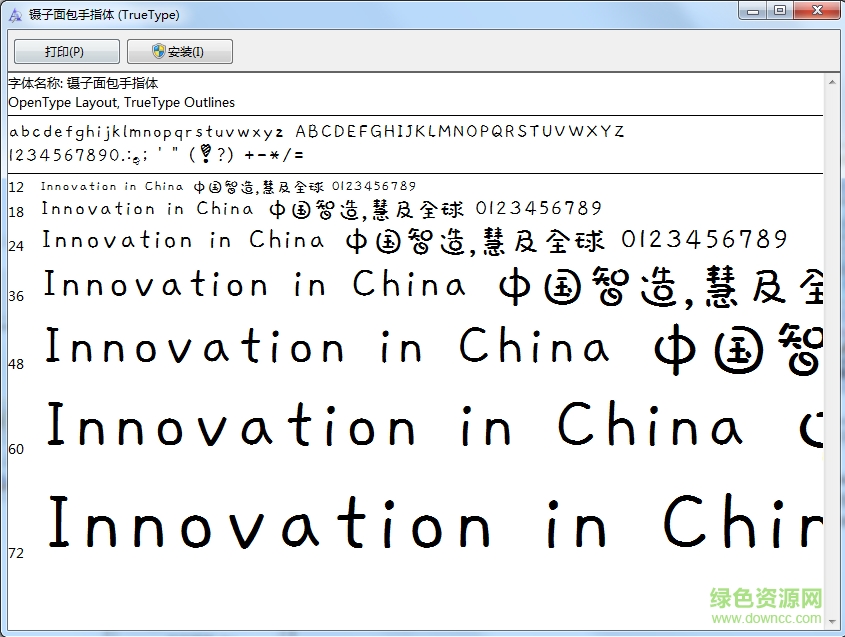
软件介绍 软件标签: 面包萌手指 卡通字体 面包萌手指是一款超卡哇伊的艺术字体,高仿面包的造型充满了童趣和可爱,让你感受各种小面包在字里行间的跳动,喜欢的朋友快来绿色资源网下载吧!面包萌手指字体介绍面包萌手指字体是一款卡通字体模板,该字体具有棱角圆润,字形饱满等特点,而且走着还在在字体笔画中加入了面包等图形。镊子面包萌手指安装说明常见字体安装方法:在绿色资源网下载并解压后,运行字体文件爱你,点击“安装”即可。如此种方法不适用,可将字体文件移动到C:\Windows\Fonts文件夹中。绿色资源网小编点评面包萌手指借用了面包的造型,透出一股萌萌的气质,最重要的是,看着看着就会饿了的字体还有谁?! 软件截图 上一张下一张(1 / 1) 安装详细截图 猜你喜欢 卡通字体 卡通字体 卡通字体一般都比较可爱、秀气,很多MM都很喜欢,许多公主体、萝莉体非常适合女生使用。类似卡通风格的字体有很多,其中最出名的就是华康少女字体了,还有华康童童体、娃娃体都很独特。本站制作的卡通字体下载大全,为喜爱卡通字体的朋友们收集整理了各种新颖、可爱、活泼的卡通字体,都是免费的,大家可以随意选择下载。 查看更多>> Aa小云朵想吃糖 5.90M/中文/10.0/ttf版下载 aa小软糖字体 4.37M/中文/10.0/下载 软萌甜心字体 18.26M/中文/10.0/ttf免费版下载 双初千草体 10.78M/中文/5.0/下载 花花爱彩虹字体 14.13M/中文/6.6/下载 小兔子乖乖体字体 1.75M/中文/2.0/下载 其他版本下载 标题 大小 更新日期 下载 下载地址 电脑版 镊子面包萌手指 点击报错 软件无法下载或下载后无法使用,请点击报错,谢谢! 关闭报错反馈 请描述您所遇到的错误,我们将尽快予以修正,谢谢! *必填项,请输入内容 本类最新 dreamweaver字体库 首尔南山体字体 v1.06 官方版 潮字社风云简ttf 潮字社凌渡鲲鹏简体字体 潮字社曾玉波手书简字体 微博慧心字体 相关文章 IIS7 支持html页面包含(include)html页面 IIS设置与代码编写 常见内存故障 金手指保养很重要 D-Link手把手指点你怎样防“蹭网” 用户评论 热门评论 最新评论 发表评论 查看所有评论(0) 昵称: 请不要评论无意义或脏话,我们所有评论会有人工审核. 字数: 0/500 (您的评论需要经过审核才能显示)